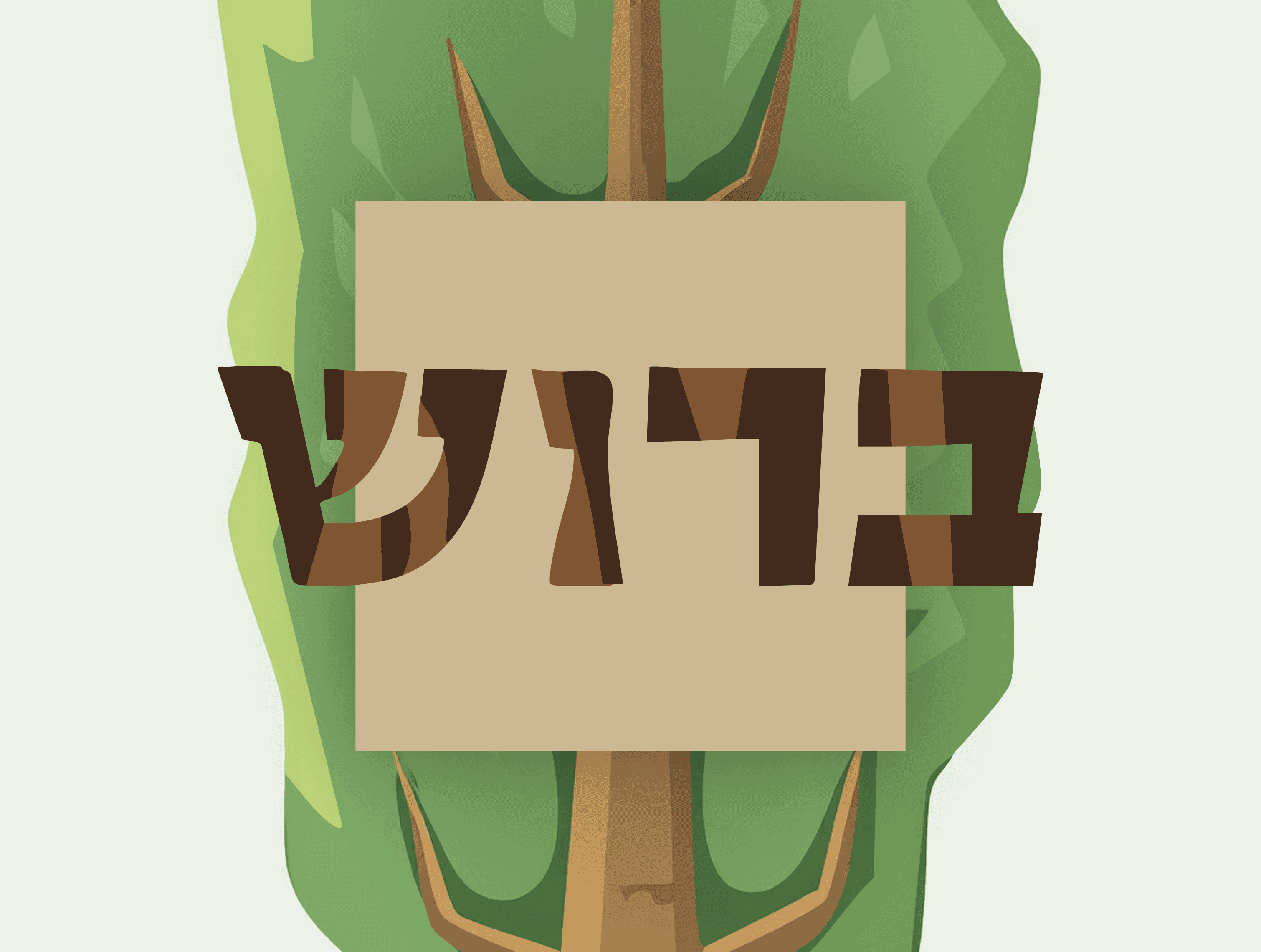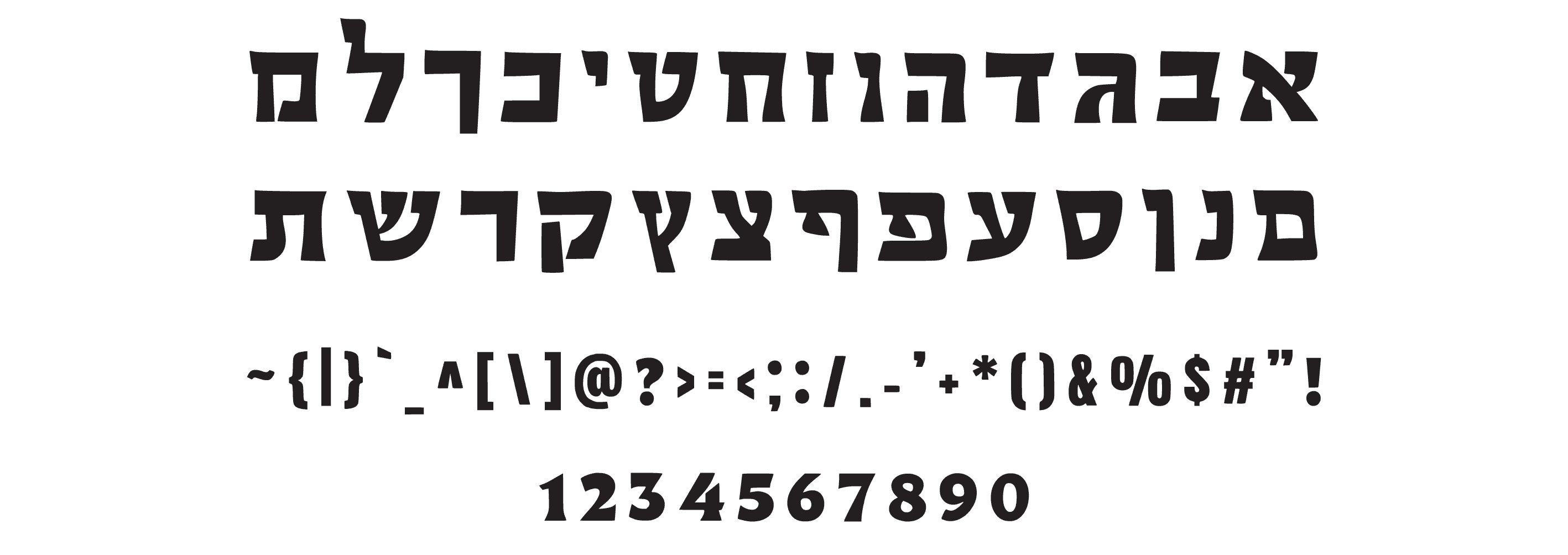
פונט ברוש
פונט עברי עבה וטבעי, עם מראה מחוספס ואותנטי, מושלם למותגי טבע ובוטיק.
ברוש — פונט עם שורשים
פונט ברוש נולד מהקרקע — הוא גס, חזק ומלא נוכחות, עם קווים שמזכירים עץ גולמי, חריטות ידניות ותחושת טבע אמיתית.
כל אות בפונט הזה מרגישה כמו שלט כפרי, תבליט עץ מגולף, או תווית של מוצר בוטיק בעבודת יד.
הוא מושלם למי שמחפש להעביר תחושה של אותנטיות, עוצמה וחיבור לאדמה ולעבודת כפיים, ומתאים לעולמות של טבע, אוכל, טיולים ומיתוגים כפריים.
איפה הוא מרגיש בבית?
🌿 לוגואים למוצרים בעבודת יד
🍞 תוויות לאוכל כפרי או טבעי
🪵 שלטי חנויות בוטיק וגלריות
🏕️ עיצובי טיולים, מחנאות ופסטיבלים בטבע
למי הוא מתאים?
למעצבים ומותגים שרוצים להכניס לעיצוב ניחוח של טבע, אותנטיות, עבודת יד וחום ישראלי כפרי.